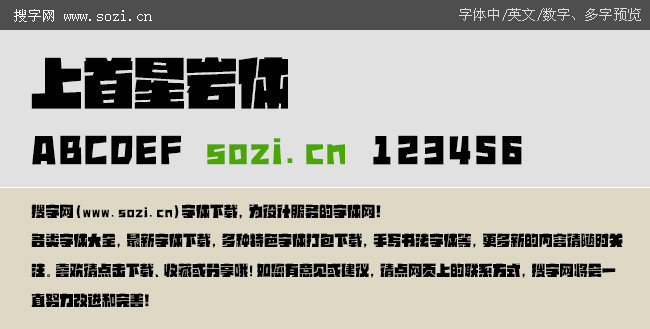
上首星巖體
搜字網(wǎng)給大家提供一款上首星巖體中文字體下載,上首星巖體是由上首造字出品的藝術(shù)字體,這款字體一個個漢字猶如一塊塊巖石緊緊拼湊,筆畫與筆畫之間形成的間隙像極了滿天的繁星,又如滿天繁星劃破天際,字體別致、筆畫獨(dú)特是此套字庫的亮點(diǎn)。適用于海報設(shè)計、兒童包裝、畫冊書籍等廣告設(shè)計。